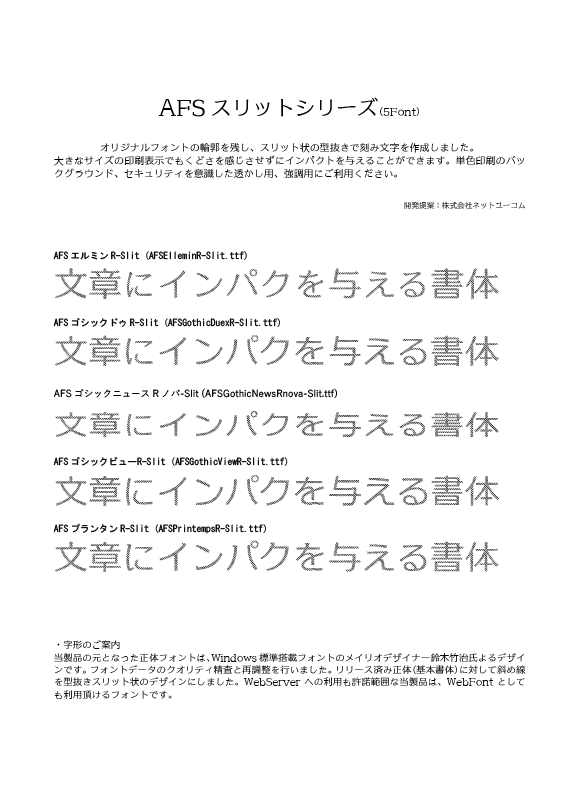
※プレビューフォントは「AFS エルミンR-Slit」です。
AFS スリットシリーズ(5Font)は、オリジナルフォントの輪郭を残し、スリット状の型抜きで刻み文字を作成しました。
大きなサイズの印刷表示でもくどさを感じさせずにインパクトを与えることができます。
単色印刷のバックグラウンド、セキュリティを意識した透かし用、強調用にご利用ください。